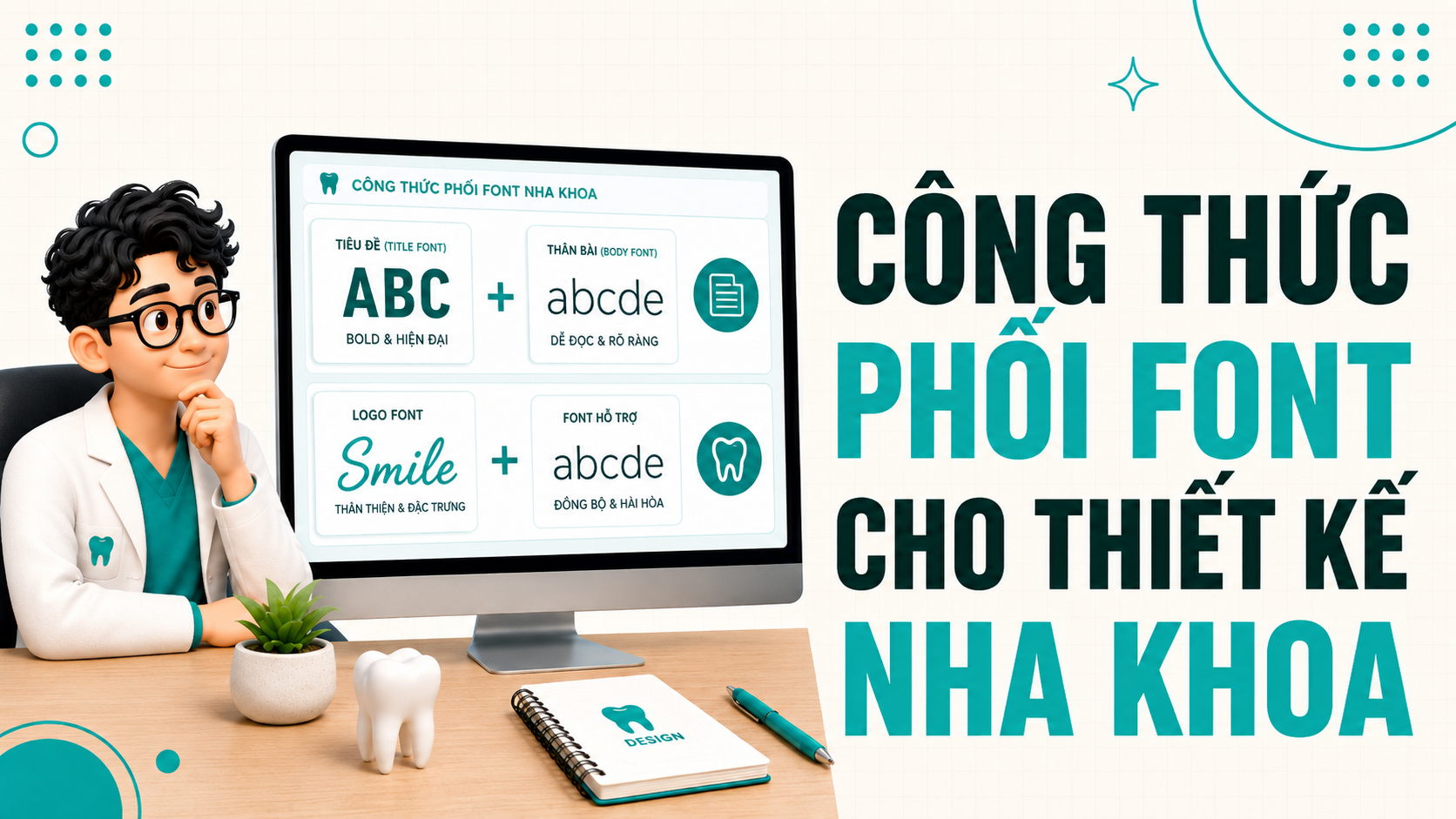
Font chữ nha khoa: gợi ý font đẹp cho phòng khám, logo và banner
Gợi ý font chữ nha khoa TH Việt hóa cho logo phòng khám, bảng giá, banner, website, nha khoa thẩm mỹ và thiết kế trẻ em.
Thiết kế nha khoa cần tạo cảm giác sạch sẽ, tin cậy và thân thiện. Khách hàng khi nhìn vào logo, bảng giá, banner, website hay bài đăng Facebook của phòng khám thường đánh giá rất nhanh: phòng khám có chuyên nghiệp không, dịch vụ có đáng tin không, thương hiệu có phù hợp với nhu cầu của họ không. Font chữ là một phần quan trọng trong cảm nhận đó.
Một font chữ nha khoa đẹp không nên quá cầu kỳ. Với lĩnh vực chăm sóc sức khỏe, font cần rõ ràng, dễ đọc và không gây cảm giác nặng nề. Tuy nhiên, mỗi mô hình nha khoa lại cần sắc thái khác nhau: nha khoa trẻ em cần thân thiện, nha khoa thẩm mỹ cần sang, nha khoa công nghệ cao cần hiện đại, còn phòng khám gia đình cần gần gũi.
Bài viết này gợi ý các font TH Việt hóa phù hợp cho thiết kế nha khoa: logo phòng khám, bảng giá dịch vụ, poster khuyến mãi, landing page, brochure, thẻ hẹn, voucher và nội dung social media.
Vì sao cần chọn đúng font chữ nha khoa
Nếu phòng khám muốn truyền tải sự an toàn và chuyên môn, hãy ưu tiên sans serif rõ ràng hoặc serif hiện đại. Những nhóm font này giúp thông tin dịch vụ như niềng răng, tẩy trắng, implant, bọc sứ, trám răng, khám tổng quát được đọc nhanh và có độ tin cậy.
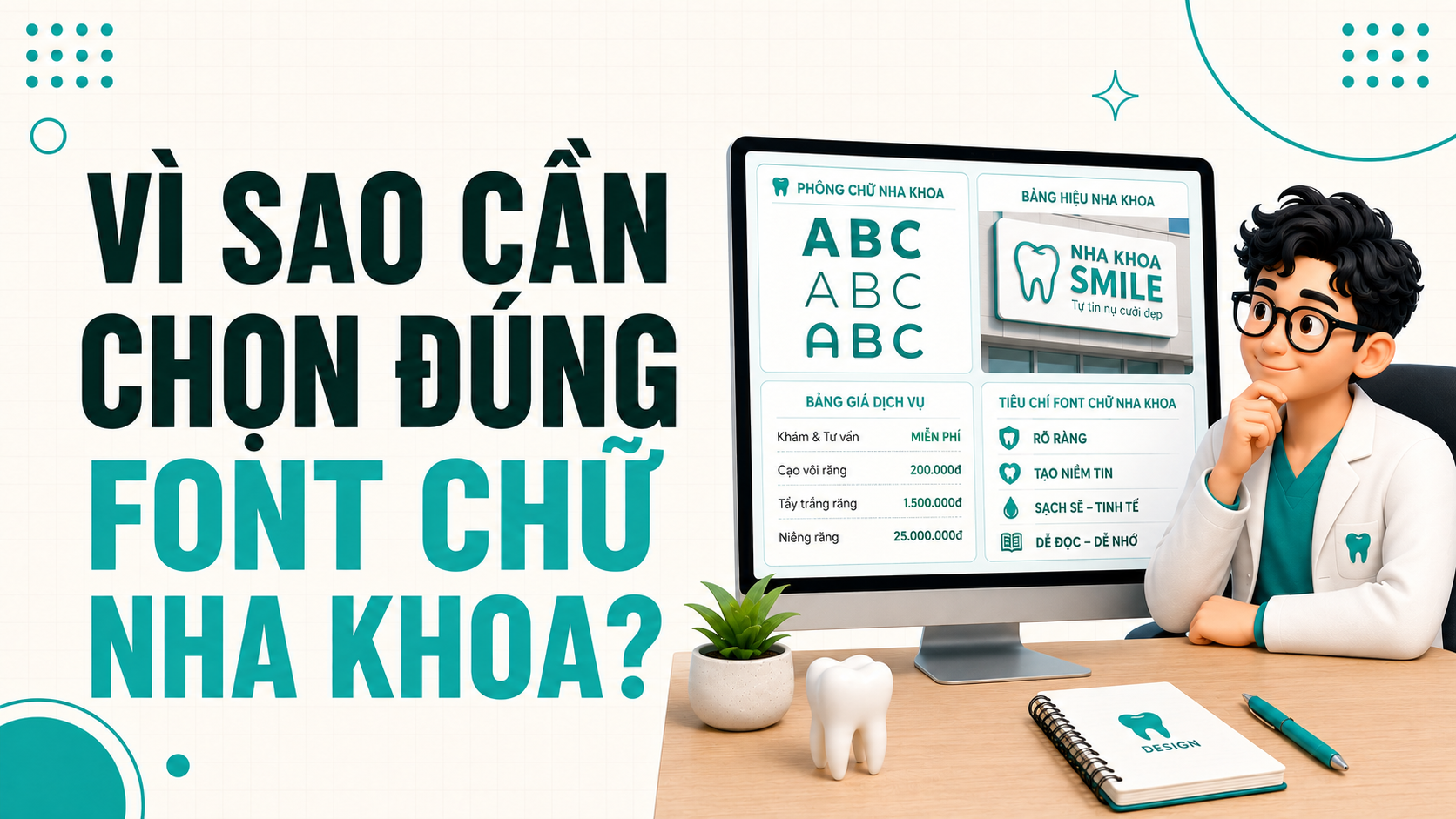
Nếu phòng khám hướng đến nha khoa thẩm mỹ, font có thể mềm và sang hơn. Serif thanh lịch, font thẩm mỹ hoặc sans serif tối giản sẽ giúp thương hiệu trông cao cấp hơn, đặc biệt khi dùng trên landing page, bảng giá veneer, răng sứ hoặc thiết kế smile makeover.
Nếu làm nha khoa trẻ em, font nên bo tròn, thân thiện và vui vừa đủ. Đừng dùng font quá nghịch cho thông tin quan trọng, nhưng có thể dùng ở poster khám răng cho bé, sticker, hướng dẫn vệ sinh răng miệng hoặc góc tư vấn phụ huynh.
Cách chọn font nha khoa theo thiết kế?
Logo nha khoa cần đơn giản và bền. Font logo nên rõ hình chữ, không lỗi dấu tiếng Việt và vẫn nhận diện được khi thu nhỏ trên avatar, thẻ hẹn hoặc biển hiệu. Nếu logo dùng font quá mảnh, khi in trên decal hoặc bảng hiệu có thể bị mất chi tiết.
Website và landing page nha khoa cần font dễ đọc cho nội dung dài. Các phần giới thiệu bác sĩ, quy trình điều trị, bảng giá, cam kết bảo hành, câu hỏi thường gặp và feedback khách hàng không nên dùng font trang trí.
Banner quảng cáo nha khoa cần font mạnh hơn một chút để tạo chú ý. Các cụm như "khám răng tổng quát", "tẩy trắng răng", "niềng răng trả góp", "ưu đãi implant" cần nổi bật nhưng vẫn giữ cảm giác y tế sạch và đáng tin.
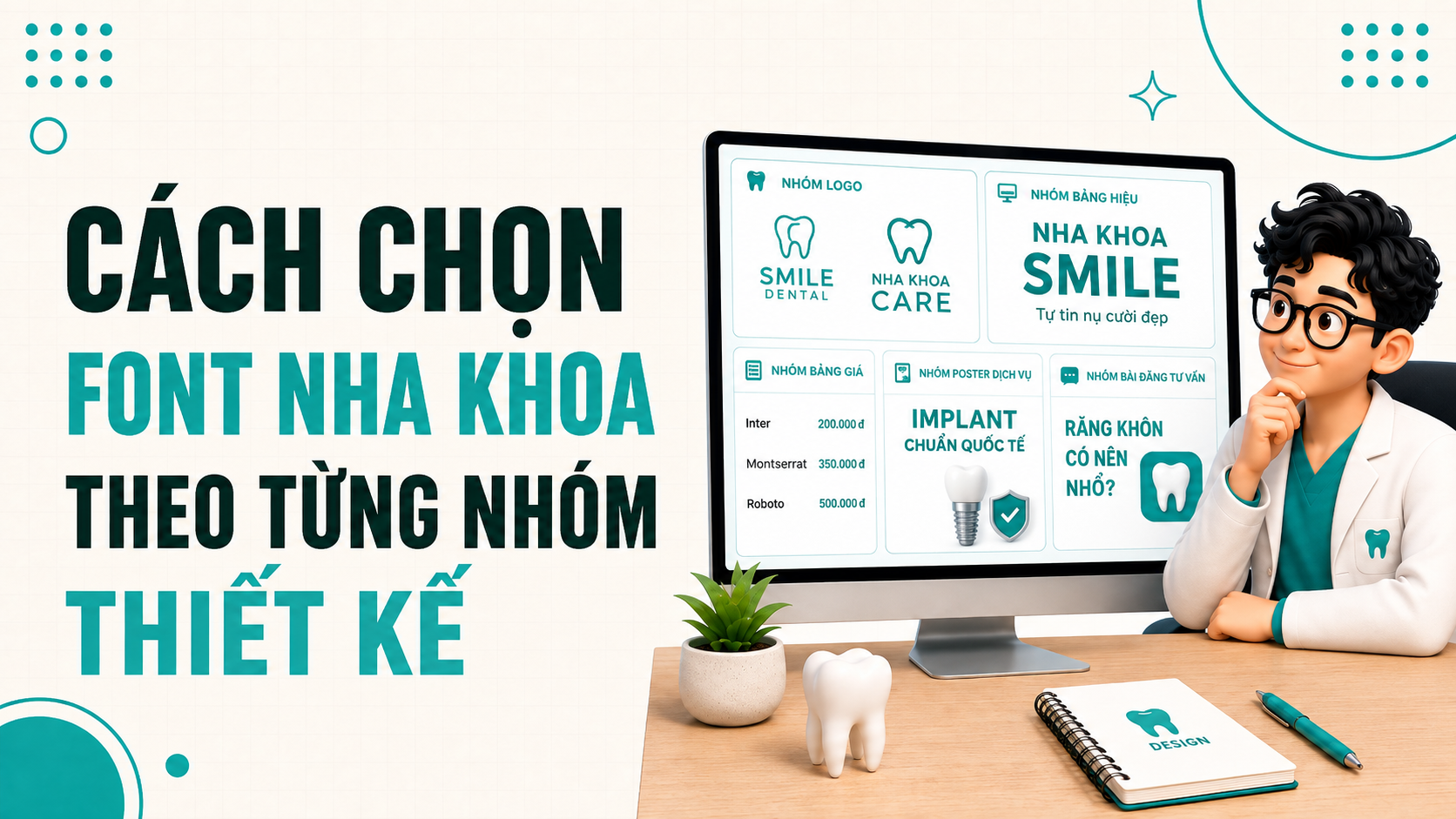
Gợi ý font TH Việt hóa đẹp cho thiết kế nha khoa
Các font dưới đây được chọn theo nhiều nhu cầu khác nhau của phòng khám nha khoa. Bạn có thể dùng font chính cho logo/headline, sau đó phối với font dễ đọc hơn cho bảng giá, mô tả dịch vụ và nội dung tư vấn.
1. TH Algance
TH Algance là sans serif tối giản, sạch và dễ đọc, rất hợp website phòng khám, bảng giá dịch vụ, brochure, profile bác sĩ và các nội dung cần cảm giác chuyên nghiệp. Khi dùng cho nha khoa, hãy test thử tên phòng khám, tên dịch vụ, bảng giá và CTA để đảm bảo font rõ trên cả file in lẫn màn hình điện thoại.
2. TH Giabe
TH Giabe là sans serif display hiện đại, phù hợp logo phòng khám trẻ, banner ưu đãi, poster khai trương và các thiết kế nha khoa muốn có điểm nhấn rõ hơn. Khi dùng cho nha khoa, hãy test thử tên phòng khám, tên dịch vụ, bảng giá và CTA để đảm bảo font rõ trên cả file in lẫn màn hình điện thoại.
3. TH Belly & Park
TH Belly & Park là font condensed hiện đại, tiết kiệm diện tích cho banner dịch vụ, bảng giá, standee, cover Facebook và headline quảng cáo nhiều chữ. Khi dùng cho nha khoa, hãy test thử tên phòng khám, tên dịch vụ, bảng giá và CTA để đảm bảo font rõ trên cả file in lẫn màn hình điện thoại.
4. TH Revans Serif
TH Revans Serif là serif cổ điển hiện đại, hợp nha khoa thẩm mỹ, veneer, implant cao cấp, profile thương hiệu và các thiết kế cần tăng độ tin cậy. Khi dùng cho nha khoa, hãy test thử tên phòng khám, tên dịch vụ, bảng giá và CTA để đảm bảo font rõ trên cả file in lẫn màn hình điện thoại.
5. TH Selvia Genatu
TH Selvia Genatu là serif sang trọng, phù hợp landing page nha khoa thẩm mỹ, bộ nhận diện cao cấp, voucher chăm sóc răng và bài social về nụ cười đẹp. Khi dùng cho nha khoa, hãy test thử tên phòng khám, tên dịch vụ, bảng giá và CTA để đảm bảo font rõ trên cả file in lẫn màn hình điện thoại.
6. TH Valoer
TH Valoer là font thẩm mỹ tinh tế, hợp phòng khám nha khoa cao cấp, spa dental, dịch vụ whitening, bọc sứ, chỉnh nha thẩm mỹ và các ấn phẩm premium. Khi dùng cho nha khoa, hãy test thử tên phòng khám, tên dịch vụ, bảng giá và CTA để đảm bảo font rõ trên cả file in lẫn màn hình điện thoại.
Font chữ nha khoa nên tạo cảm giác sạch, tin cậy, dễ đọc và phù hợp với mô hình phòng khám. Với nha khoa thẩm mỹ, font có thể sang hơn; với nha khoa trẻ em, font có thể thân thiện hơn; với website và bảng giá, độ rõ vẫn là ưu tiên số một.
Các font TH Việt hóa trong bài là gợi ý thực tế để thiết kế logo, banner, website, bảng giá và tài liệu truyền thông nha khoa. Hãy tải font phù hợp, test tiếng Việt kỹ và phối font nhất quán trước khi triển khai bộ nhận diện.